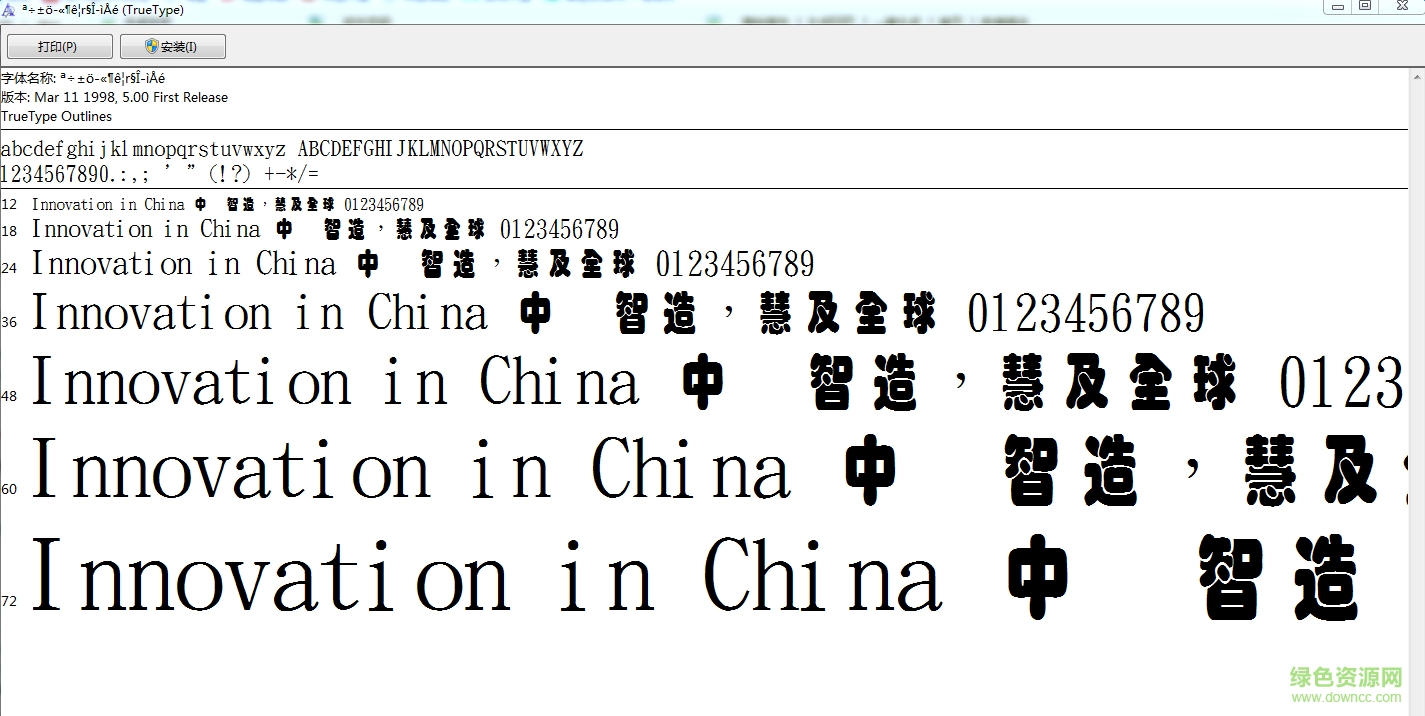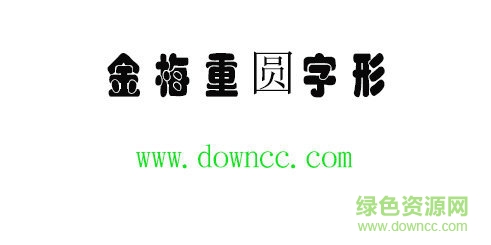
金梅重圓字形原體字體是一款金梅類圓形原體字體軟件,圓體字給人非常圓滑的感覺(jué),深受廣大書(shū)法家的喜愛(ài),而且其被使用的范圍也非常的廣泛,也深受廣大用戶的喜愛(ài),還有更多好看好用的字體盡情期待,歡迎到綠色資源網(wǎng)下載體驗(yàn)!
金梅重圓字形原體是一款金梅類圓形原體字體,字體效果比較圓滑,喜歡圓滑字體的朋友可以下載使用看看效果如何。